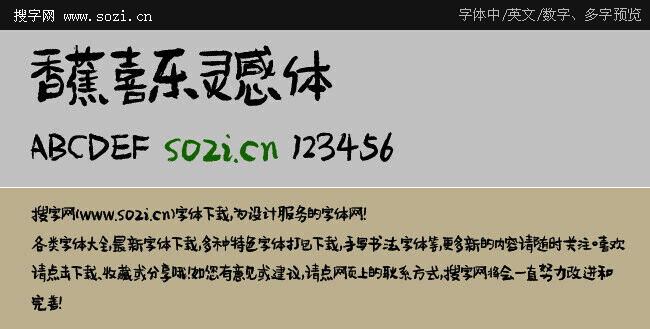
香蕉喜樂靈感體
搜字網(wǎng)提供一款香蕉喜樂靈感體中文藝術(shù)字體下載,香蕉喜樂靈感體是一款手寫風(fēng)格書法字體,安寧自在、松弛隨性是這款字體的設(shè)計(jì)構(gòu)思,筆畫平直減省,化繁為簡。恰到好處的平衡情緒與松弛感,巧中帶拙,隨意而又不失講究,是這款字體最顯著的特征。 適合包裝設(shè)計(jì)、海報(bào)設(shè)計(jì)、廣告設(shè)計(jì)等應(yīng)用。